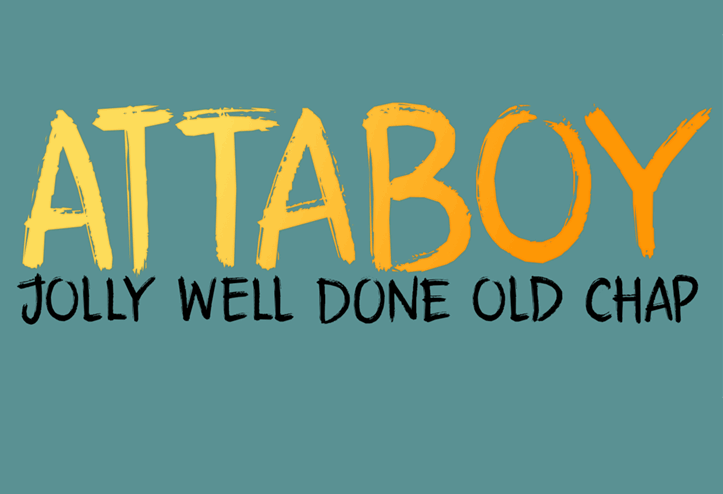
A DK Attaboy Brush Font é uma seleção elegante de letras feitas à mão que se destacam com suas linhas fluidas e seus traços delicados. Perfeita para criar um ar descontraído, essa fonte oferece um toque moderno e criativo aos designs, seja em projetos pessoais ou comerciais. Se você está procurando por uma opção única que combine elegância com personalidade, a DK Attaboy Brush Font é uma excelente escolha. Ainda melhor, ela chega ao seu dispositivo pronto para uso, permitindo que você aproveite todas as suas características sem preocupações legais. Como o próprio nome sugere, esta fonte traz um toque de descontração e irreverência à sua produção, fazendo-a se destacar entre os demais. Ao escolher a DK Attaboy Brush Font para seus projetos, você está garantindo não apenas uma experiência funcional, mas também uma expressão visual única que combina elegância com originalidade.
Designer: David Kerkhoff